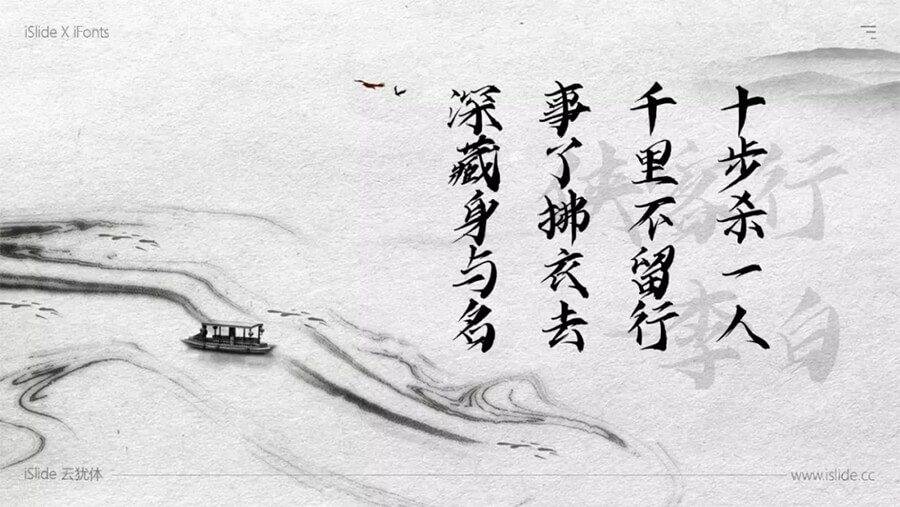
iSlide&iFonts 联合推出独家字体iSlide云犹体在秀丽毛笔字风格的基础上更加强调了字体的曲折收放变化,使得整个字体开合揖让有度,辗转腾挪,不至过于秀气婉约,婉转中铿锵有力,锋芒外露。iSlide云犹体局部的形变与外拓带来的是整体气势的叠加,兼顾了阴柔与阳刚、含蓄与强劲。露锋用笔贯彻到了字体的始终,结体紧致,大量的曲线强化了字体的动感与字形张力。欢迎喜欢iSlide云犹体的朋友前来下载使用。